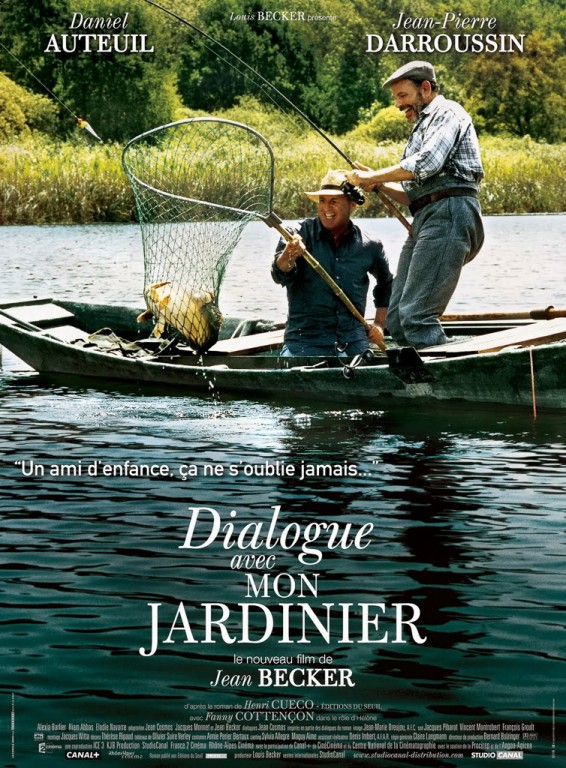
Je ne suis pas si sévère, c'est une affiche, un travail de graphiste, pas de typographe, comme la couverture d'un livre. Je regrette que le « MON » ait été composé dans un corps inférieur sans recours aux small caps, mais j'aime bien l'idée du « avec », coincé dans l'interligne. |